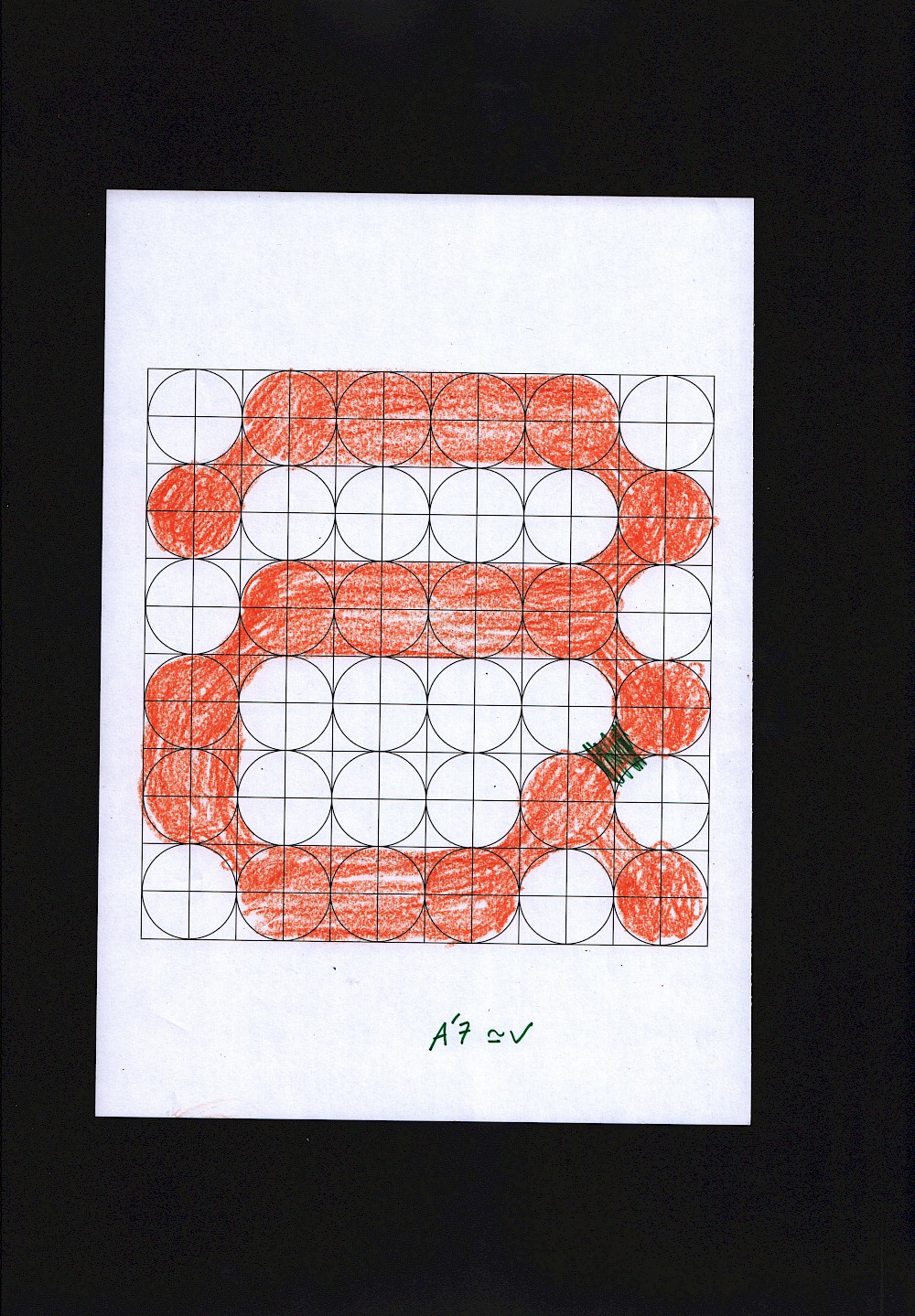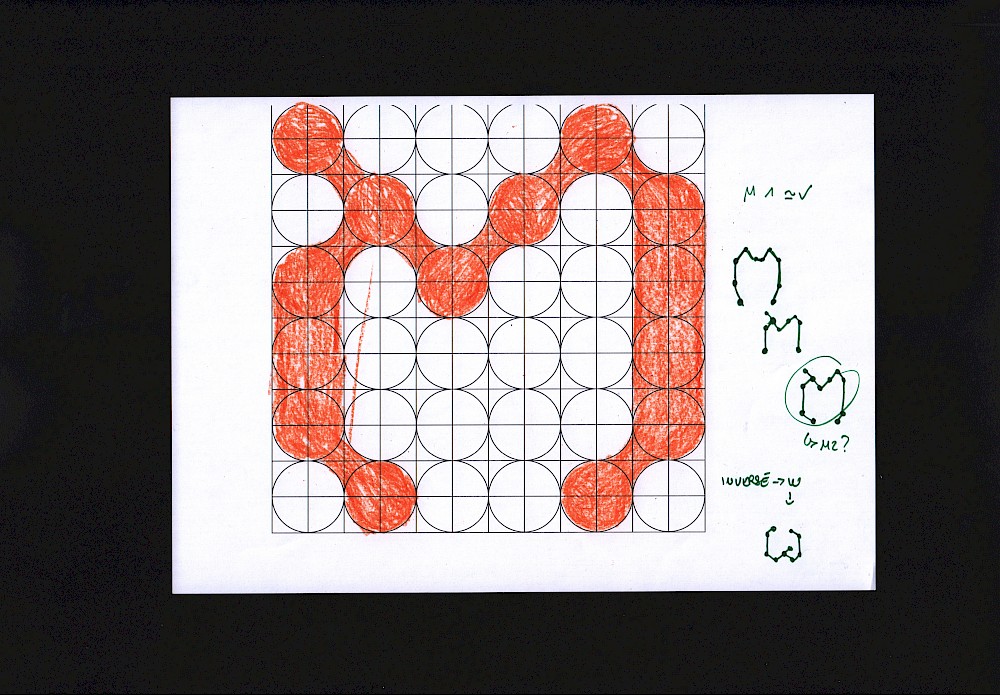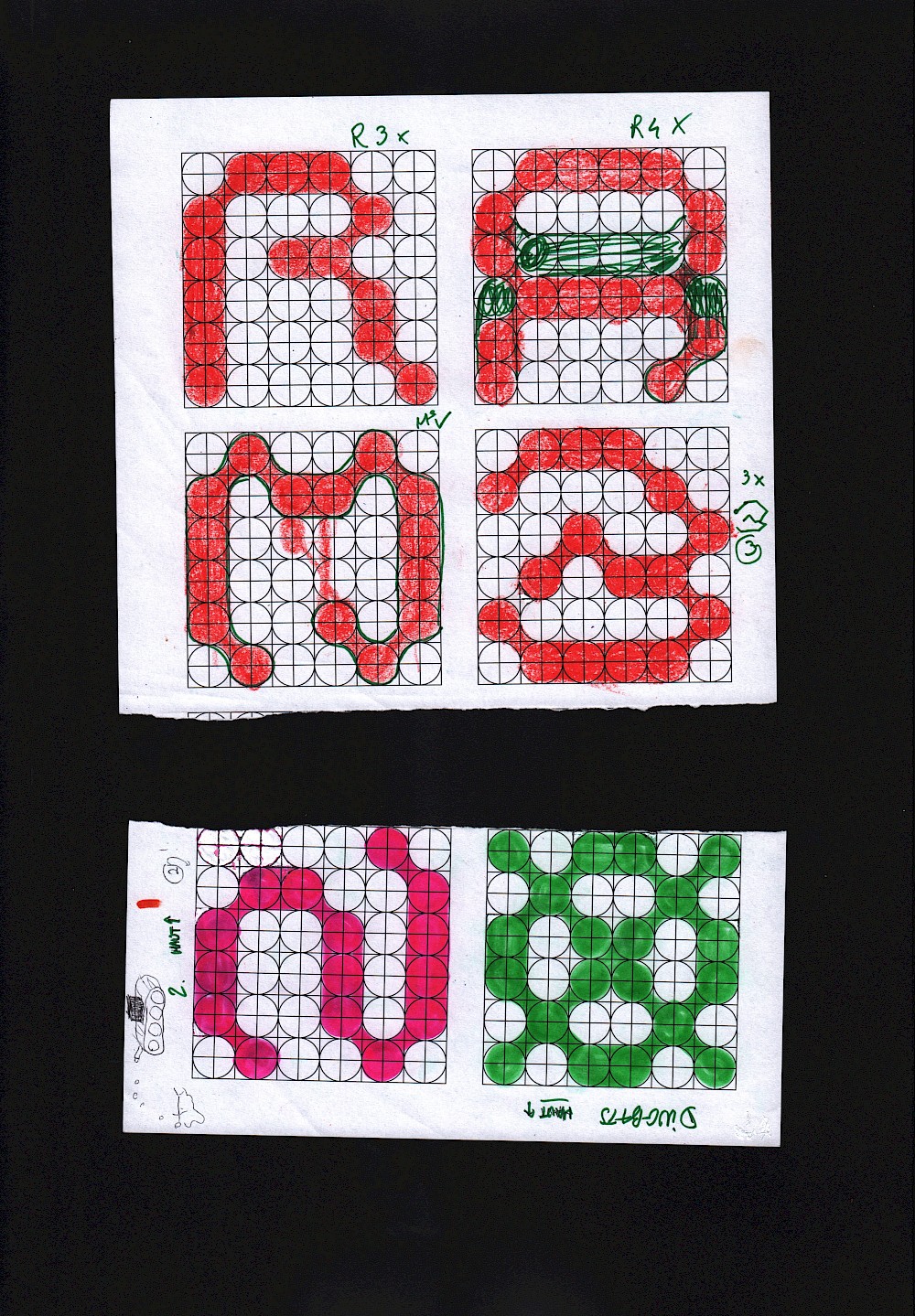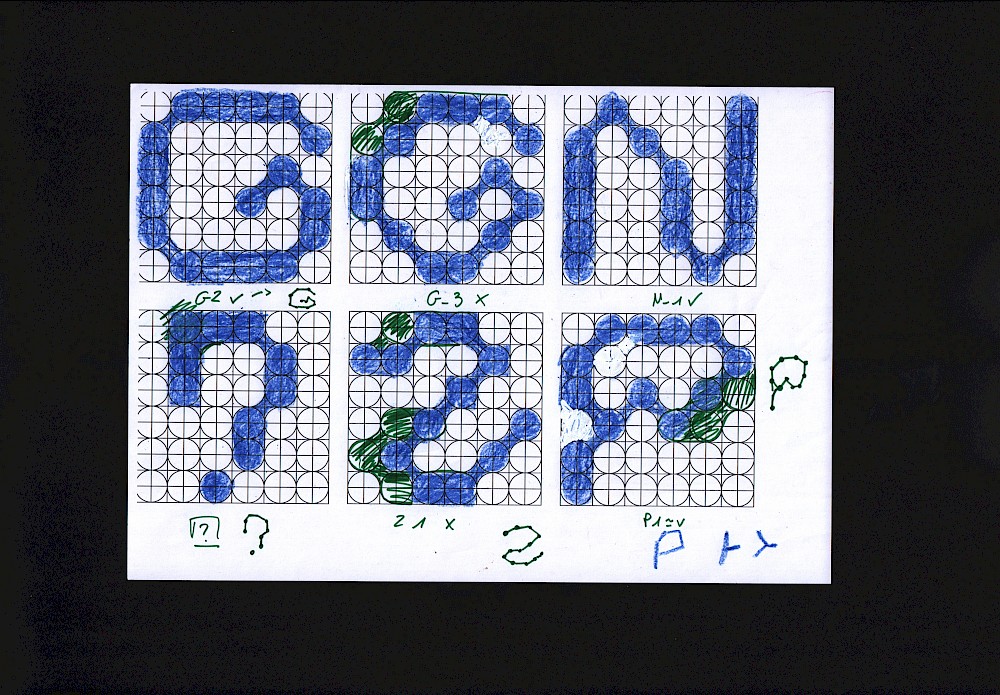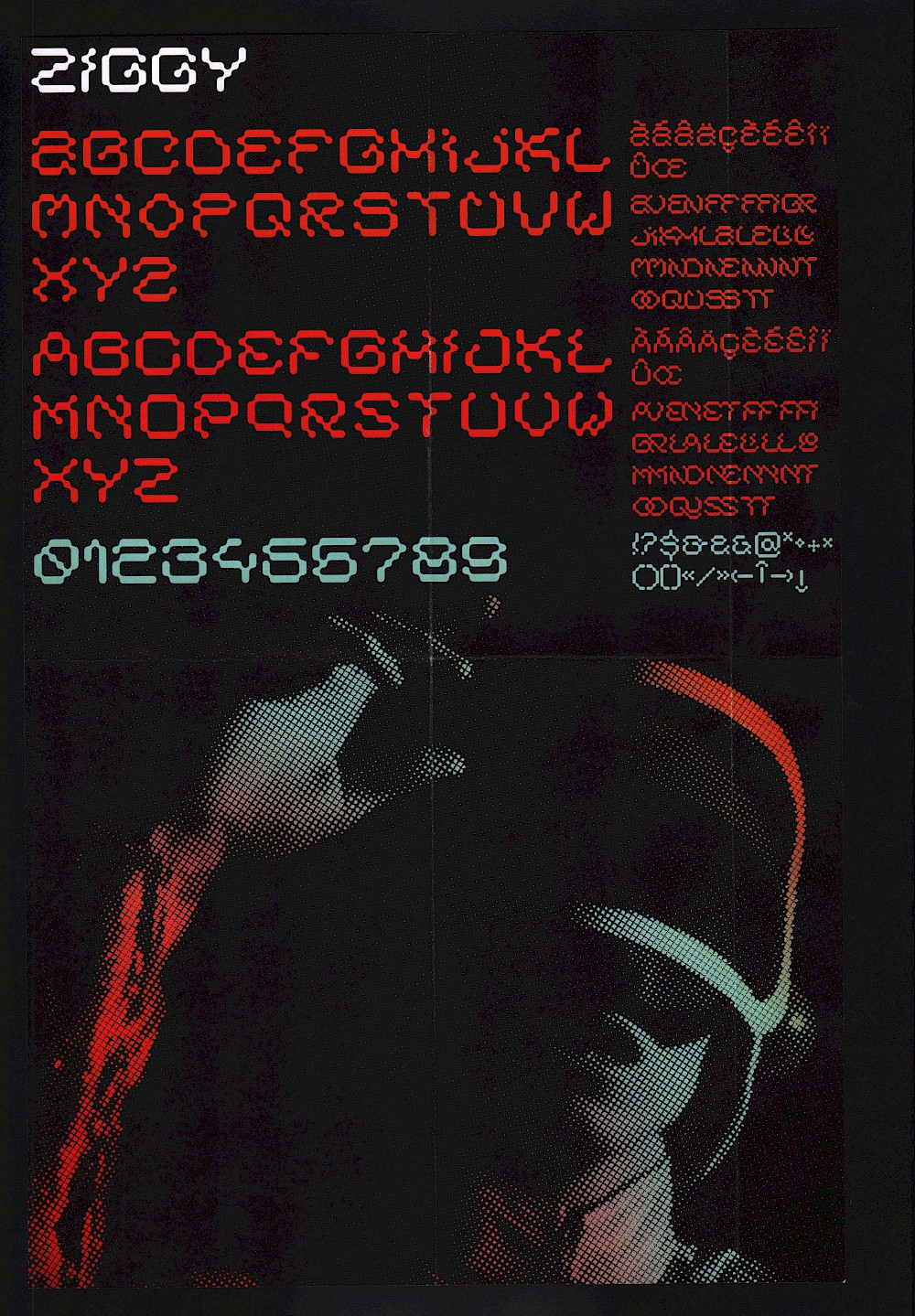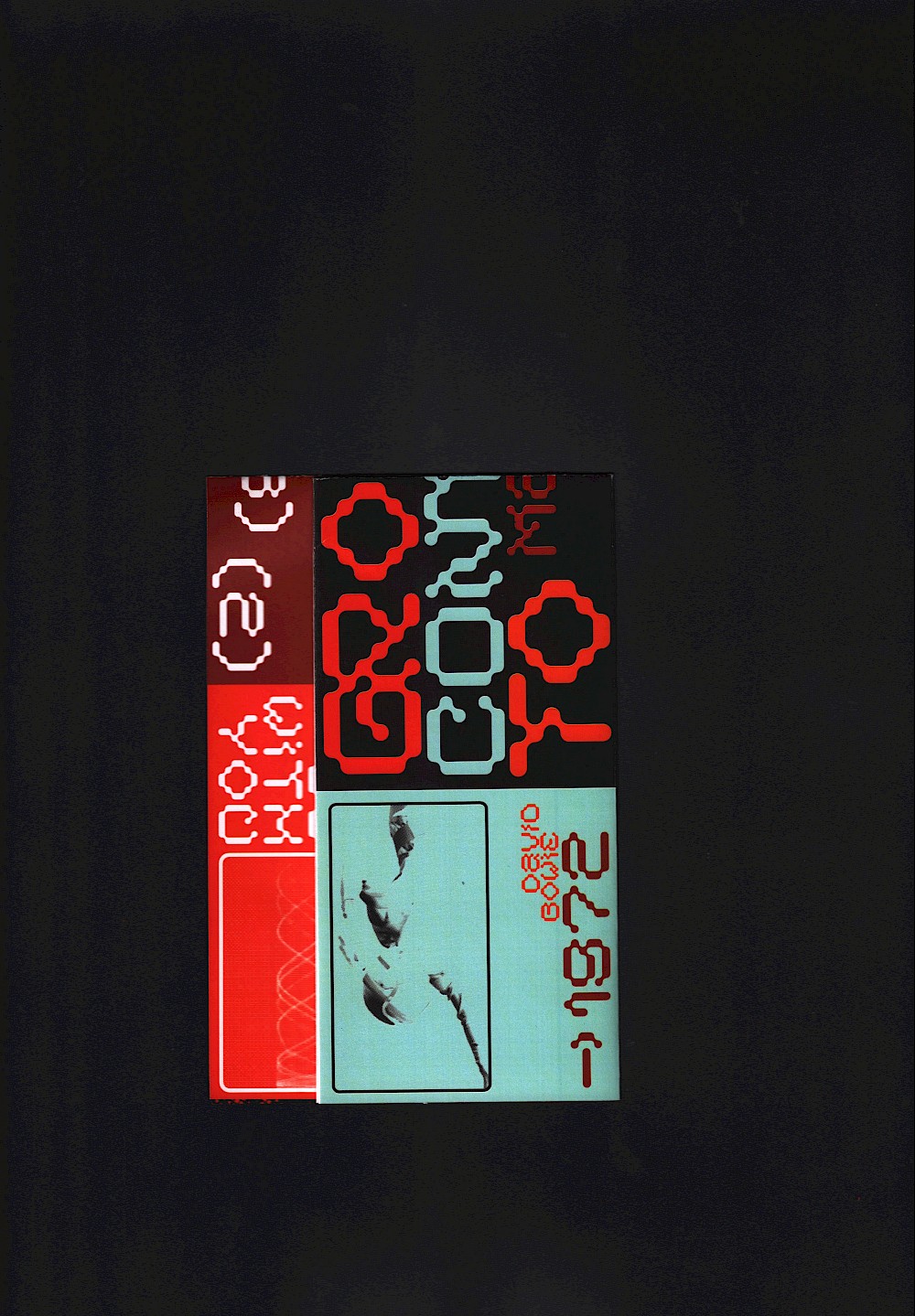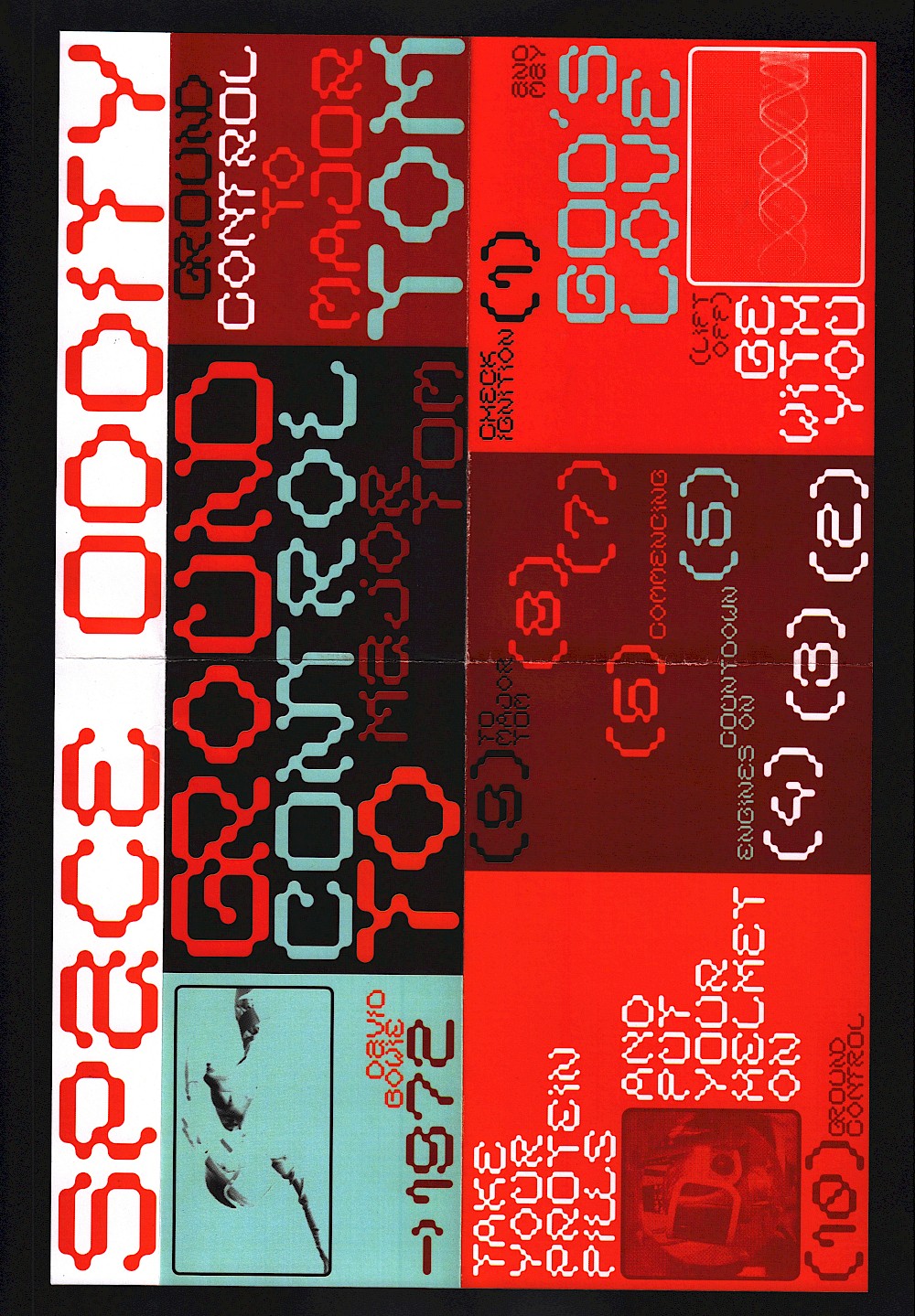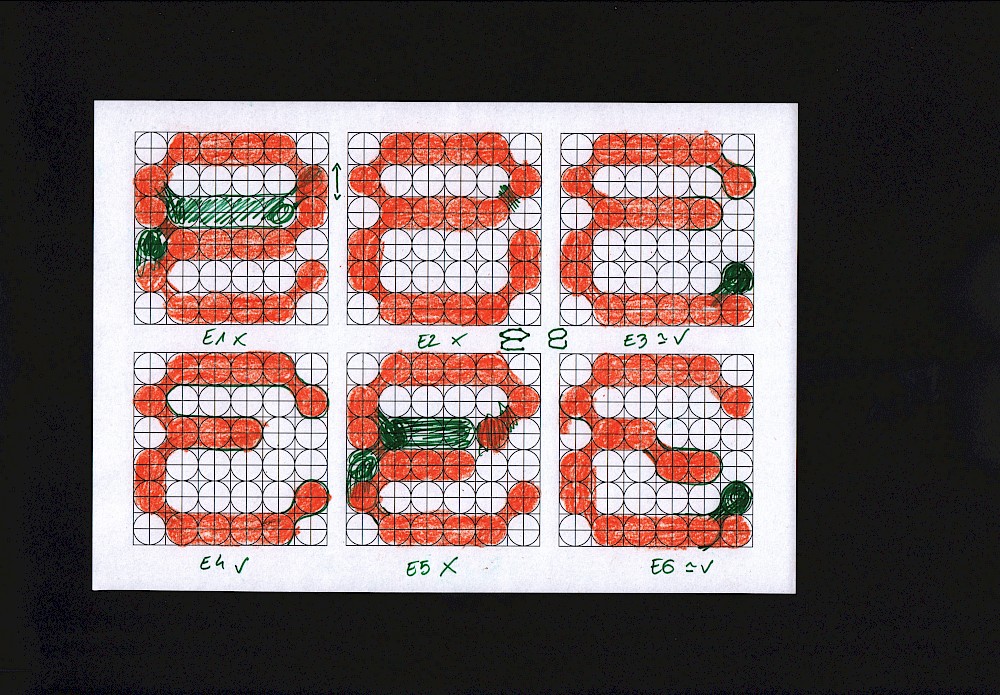
tuto: Comment pallier à la peur de se lancer dans du dessin de caractères? •Faire une grille •Colorier •Dire que c'est une typo "modulaire"
Petit visuel sur la mélodie de notre ami Ziggy, pour une typo qui finalement fait bien space opera
BikeChain — rawn, jancaissemal
En 2020 pendant le Covid, j'ai comme beaucoup, un max de temps libre. Je décide au moment de faire mon portfolio pour rentrer en DNMADe, de dessiner une font. Un peu peureux de débuter par du vrai dessin de caractères, j'ai l'idée de trouver un module qui va faciliter la construction de cette typo. D'où BikeChain, qui est crée autour d'un module rappelant le motif en huit des chaînes de vélo. ദ്ദി(˵ •̀ ᴗ - ˵ ) ✧
BikeChain